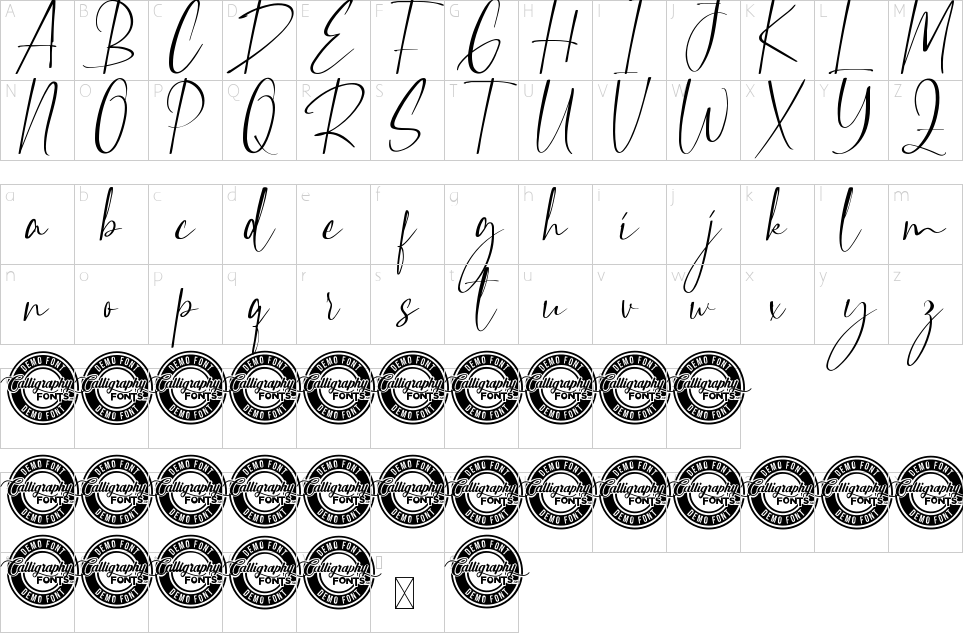
Aqui está uma descrição em português, envolvente e natural, para a página de download da fonte Magnesian do site da 1001 Free Fonts: Magnesian é uma fonte minimalista e elegante, perfeita para uso em sites, blogues e até mesmo em aplicações de design gráfico. Desenvolvida pela equipe da CalligraphyFonts, esta fonte vem em versões para Windows e Mac, permitindo que designers de todo o mundo enriqueçam seus projetos com seu charme fluido e versátil. Com um design minimalista e moderno, Magnesian oferece uma solução de fonte versátil para projetos que vão desde sites de blog até design gráfico, sem deixar de lado a elegância e o estilo de CalligraphyFonts. Se você está procurando por uma fonte que seja tanto funcional quanto bonita, Magnesian é uma excelente escolha.